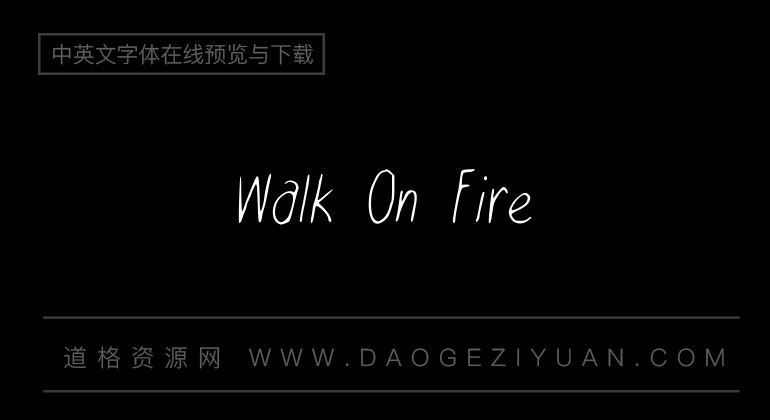
Walk On Fire
Walk On Fire 字体是一款英文手写字体,由英国设计师Steve Jackaman设计。它是一款简单而又时尚的字体,适用于各种设计项目,包括海报、商标、网页和T恤等。它的特点在于它的自然手写风格,具有轻松、活泼、温暖的感觉,可以增强设计的艺术气息。
Walk On Fire是一款非常不错的手写艺术字体,具有很好的视觉感,适合于文化类的宣传设计、商业类品牌的广告和产品包装设计以及个性化文字排版等较多场景。